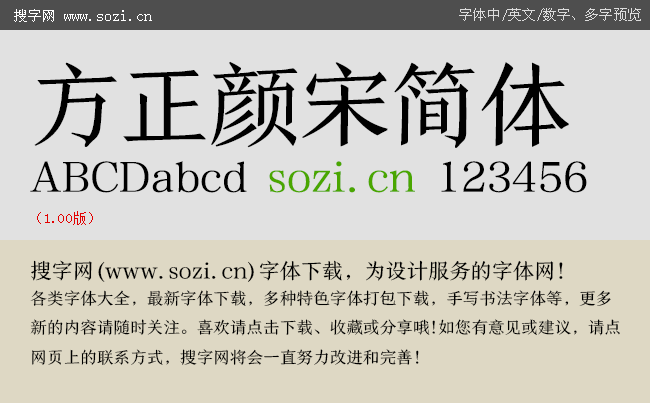
方正顏宋簡(jiǎn)體
搜字網(wǎng)給大家提供一款方正顏宋簡(jiǎn)體中文字體下載,方正顏宋字體既有宋體字形方正、結(jié)構(gòu)嚴(yán)謹(jǐn)、整齊均勻、易讀醒目的優(yōu)點(diǎn),又有著顏體豐腴雄渾、骨力遒勁、古樸厚重的韻味,與一般宋體相比增加了手寫(xiě)味道。 可用于標(biāo)題、廣告招貼、產(chǎn)品包裝,亦可作為印刷、屏幕顯示等的正文字使用。